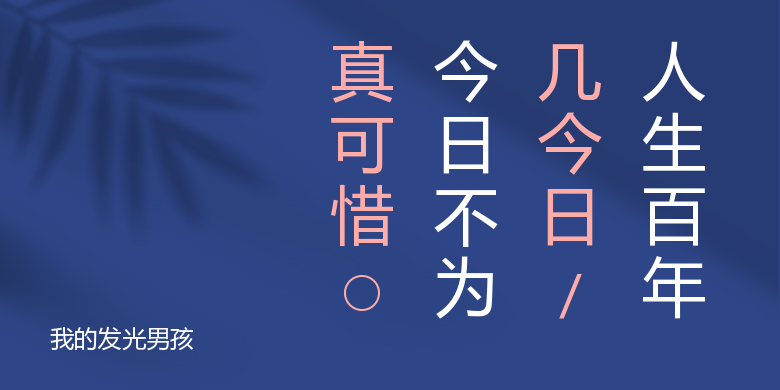
我的发光男孩
我的发光男孩,这款字体结构工整、笔画清晰,兼顾美观与易读性,适用于标题、正文、海报、包装、LOGO 等多种场景。字形优雅稳定,风格百搭耐看,适配日常排版与创意设计,让文字呈现更舒适、更具质感。我的发光男孩一笔一画,皆是细节,以均衡的比例、流畅的线条打造舒适视觉体验,字形端正大气,风格简约现代。无论是商业设计、品牌宣传还是日常排版,都能轻松驾驭,让文字更有格调与力量。我的发光男孩字体下载。